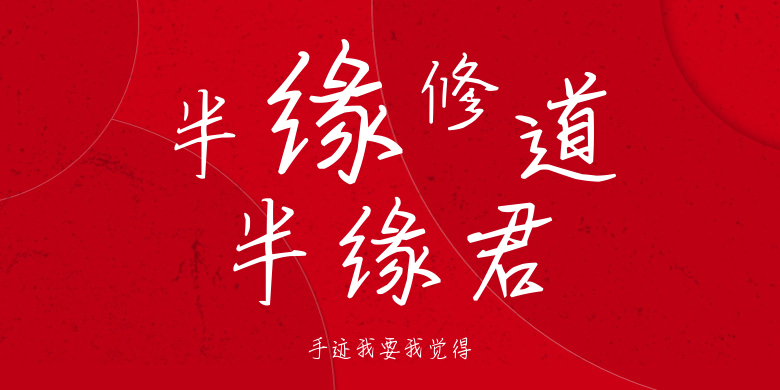
手迹我要我觉得
手迹我要我觉得,这款字体结构工整、笔画清晰,兼顾美观与易读性,适用于标题、正文、海报、包装、LOGO 等多种场景。字形优雅稳定,风格百搭耐看,适配日常排版与创意设计,让文字呈现更舒适、更具质感。手迹我要我觉得一笔一画,皆是细节,以均衡的比例、流畅的线条打造舒适视觉体验,字形端正大气,风格简约现代。无论是商业设计、品牌宣传还是日常排版,都能轻松驾驭,让文字更有格调与力量。手迹我要我觉得字体下载。